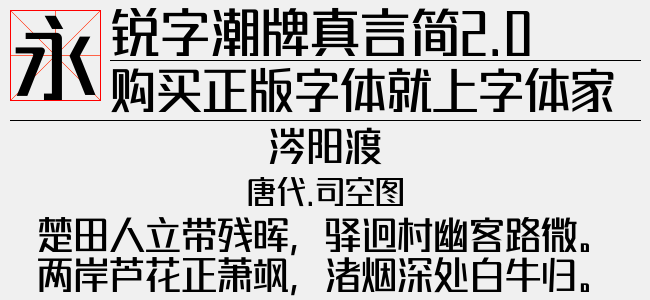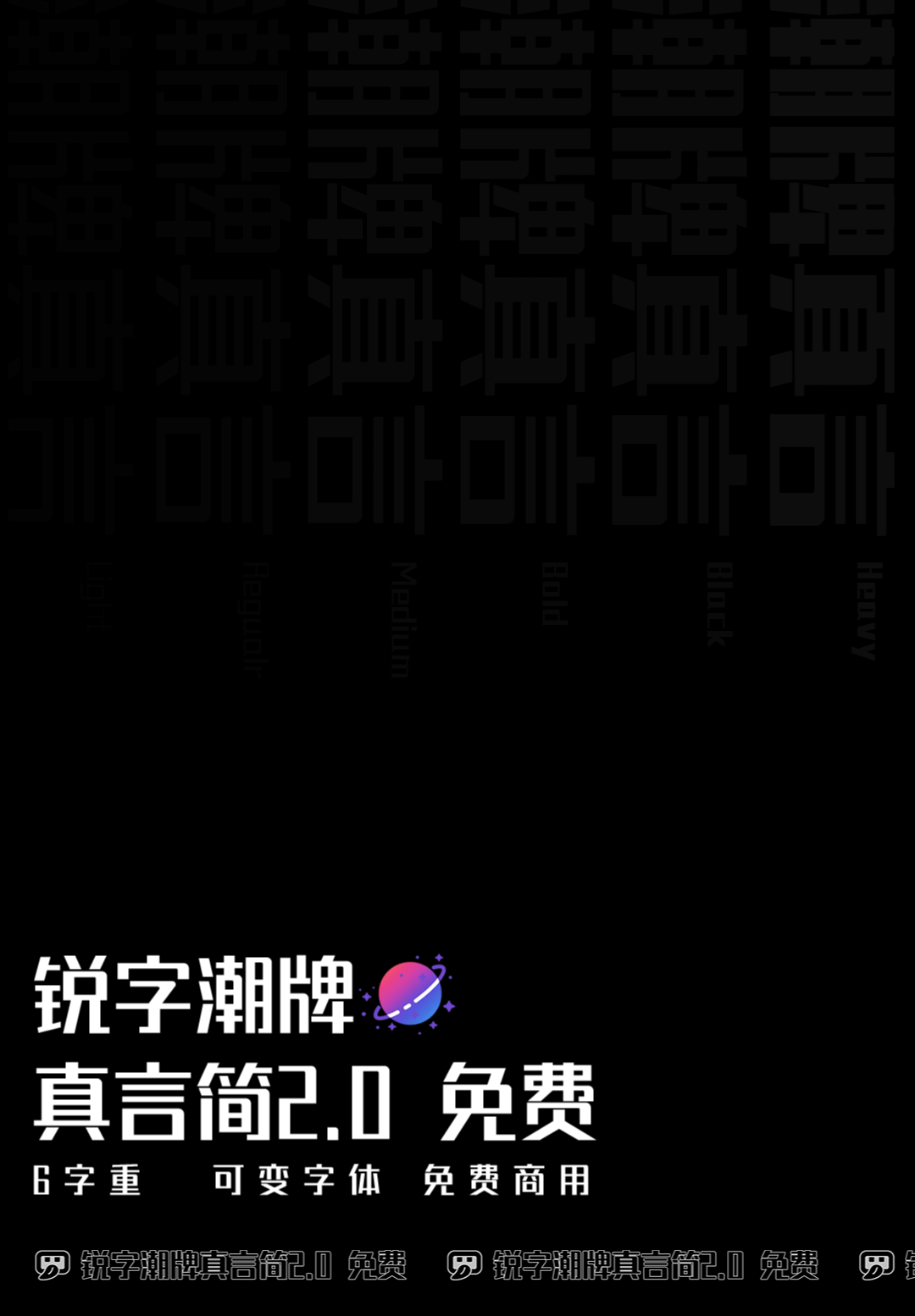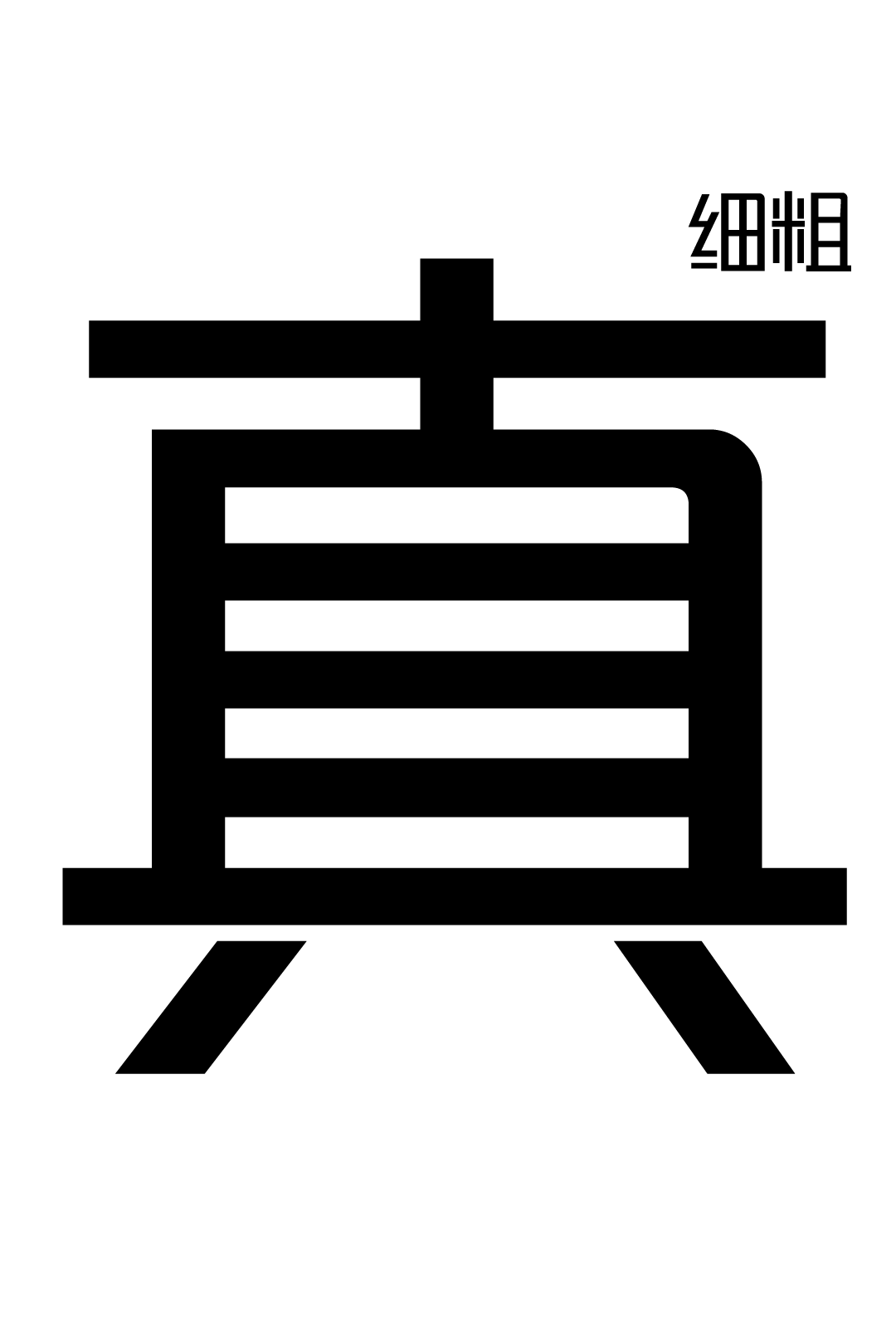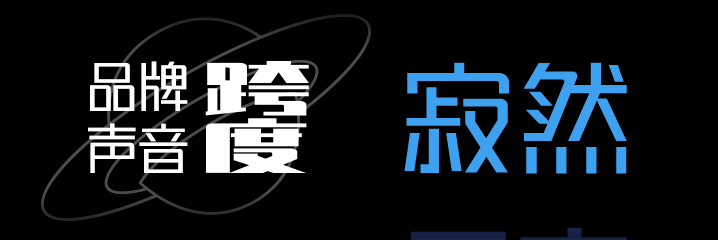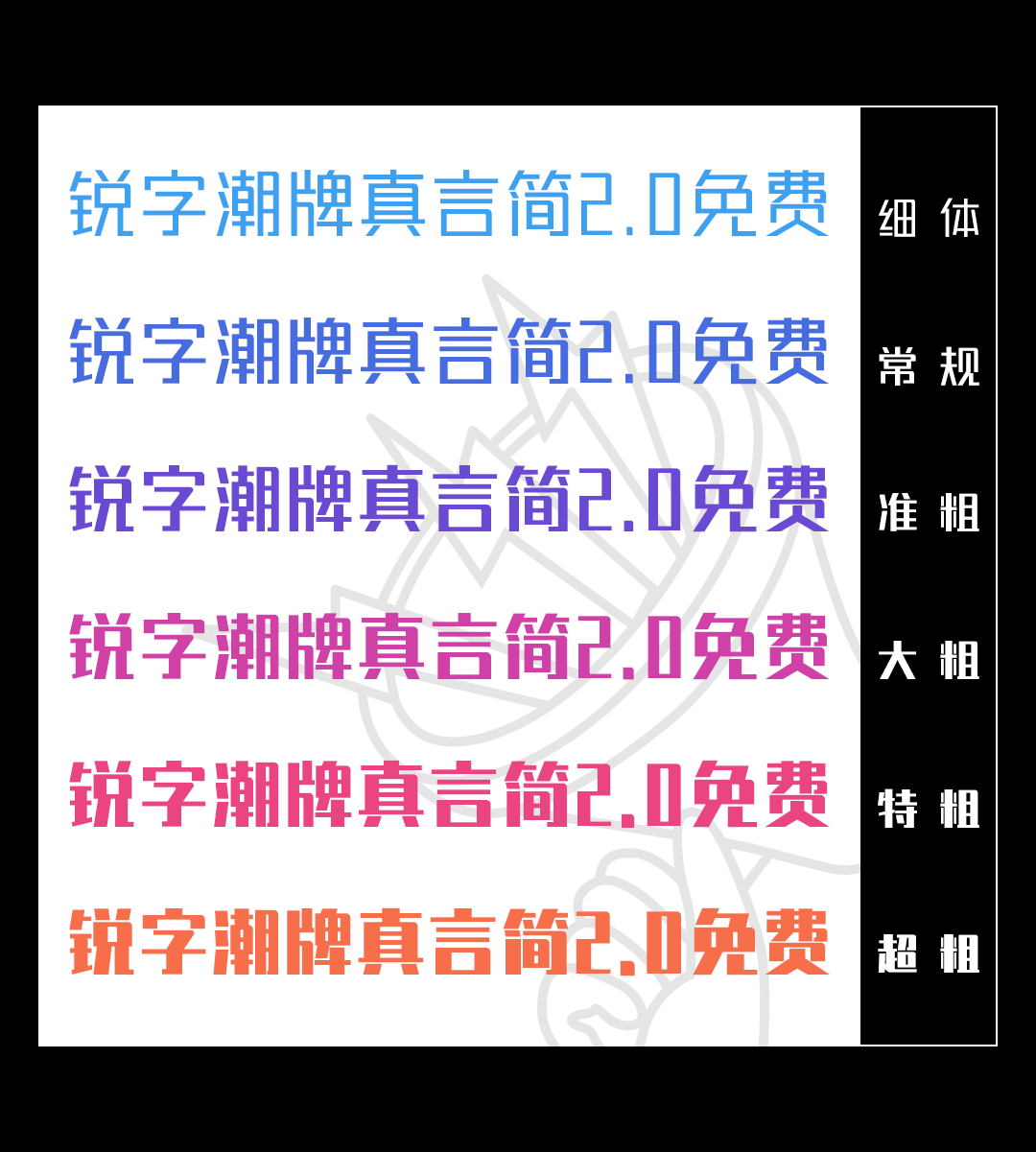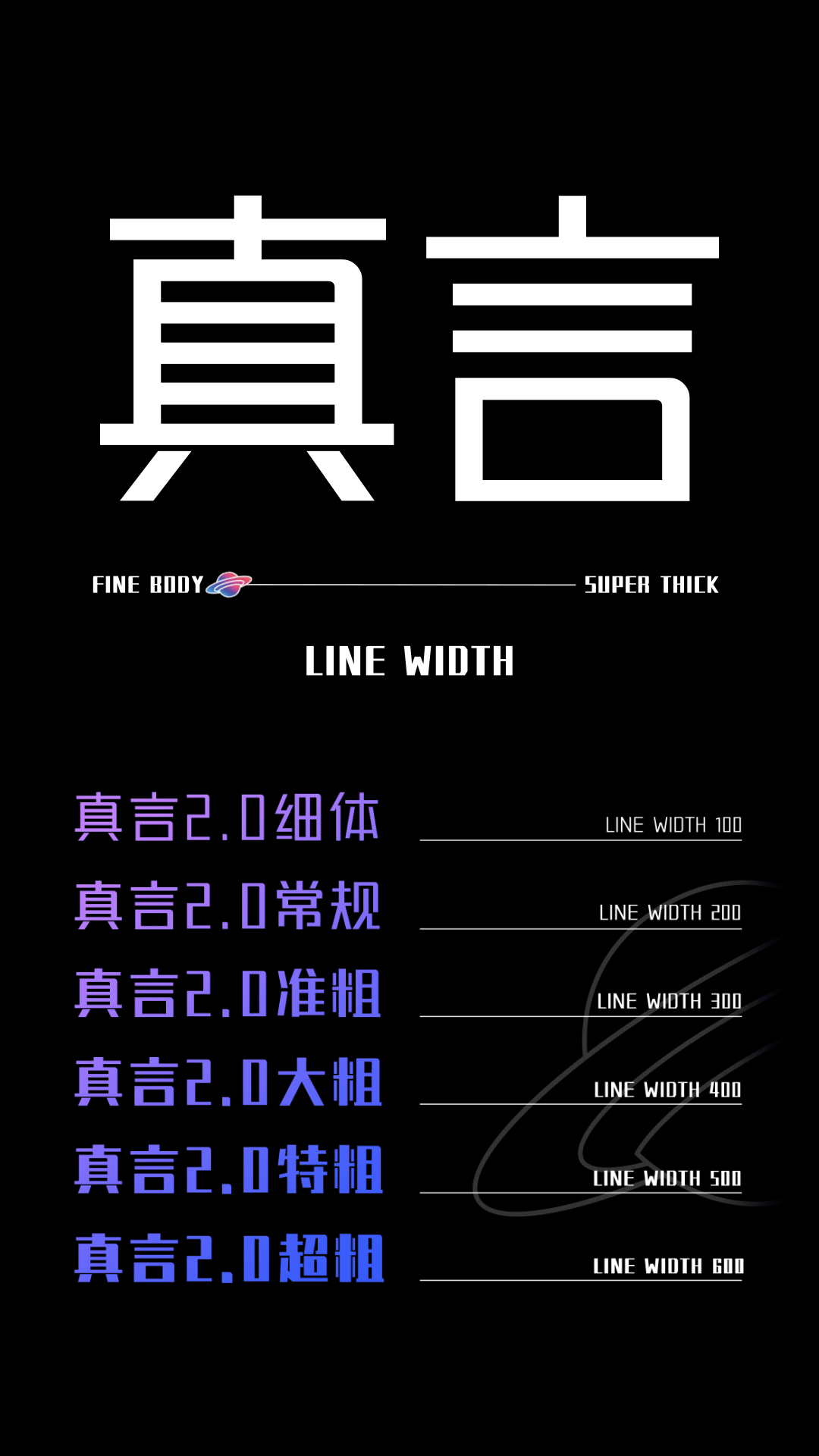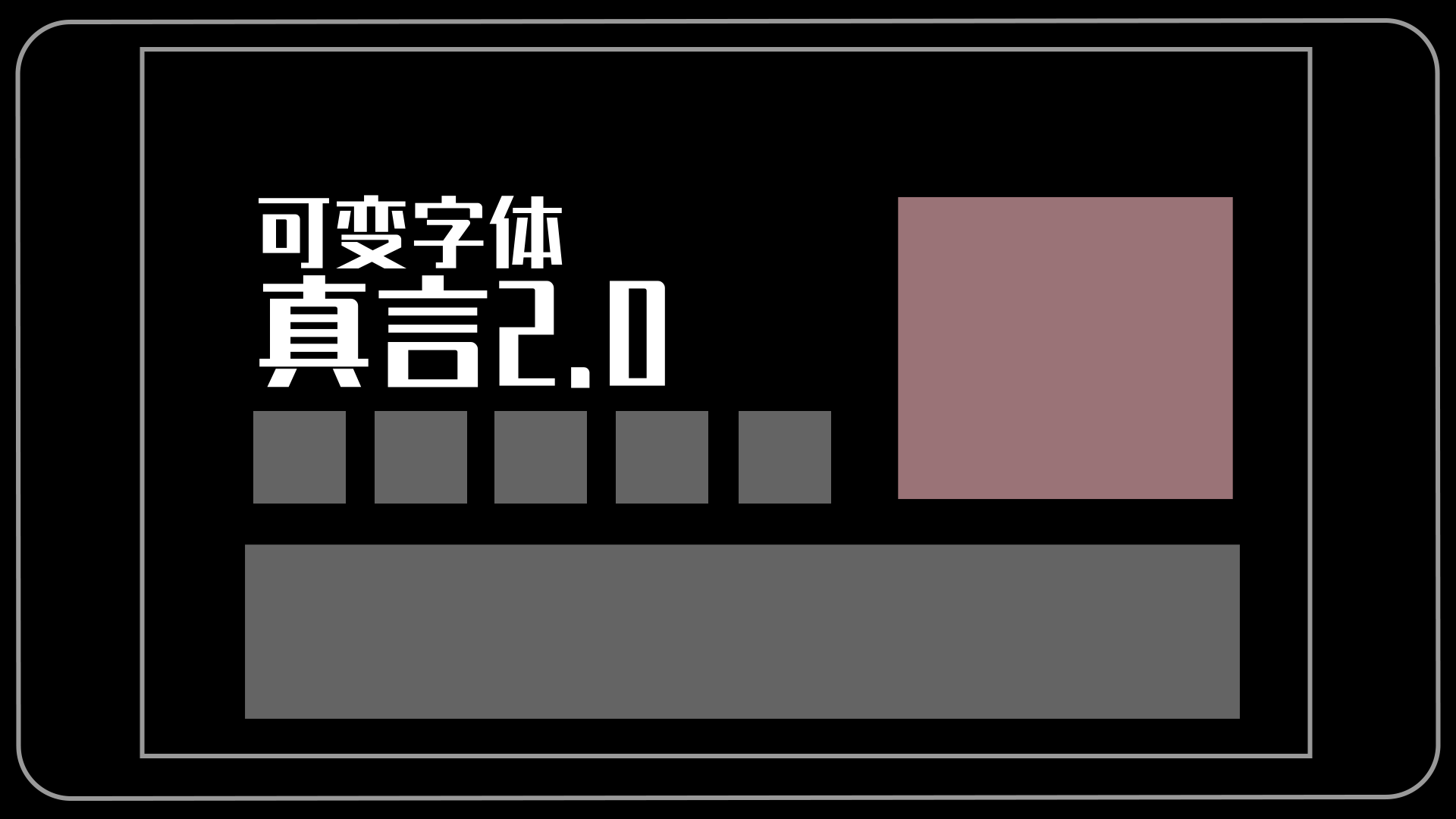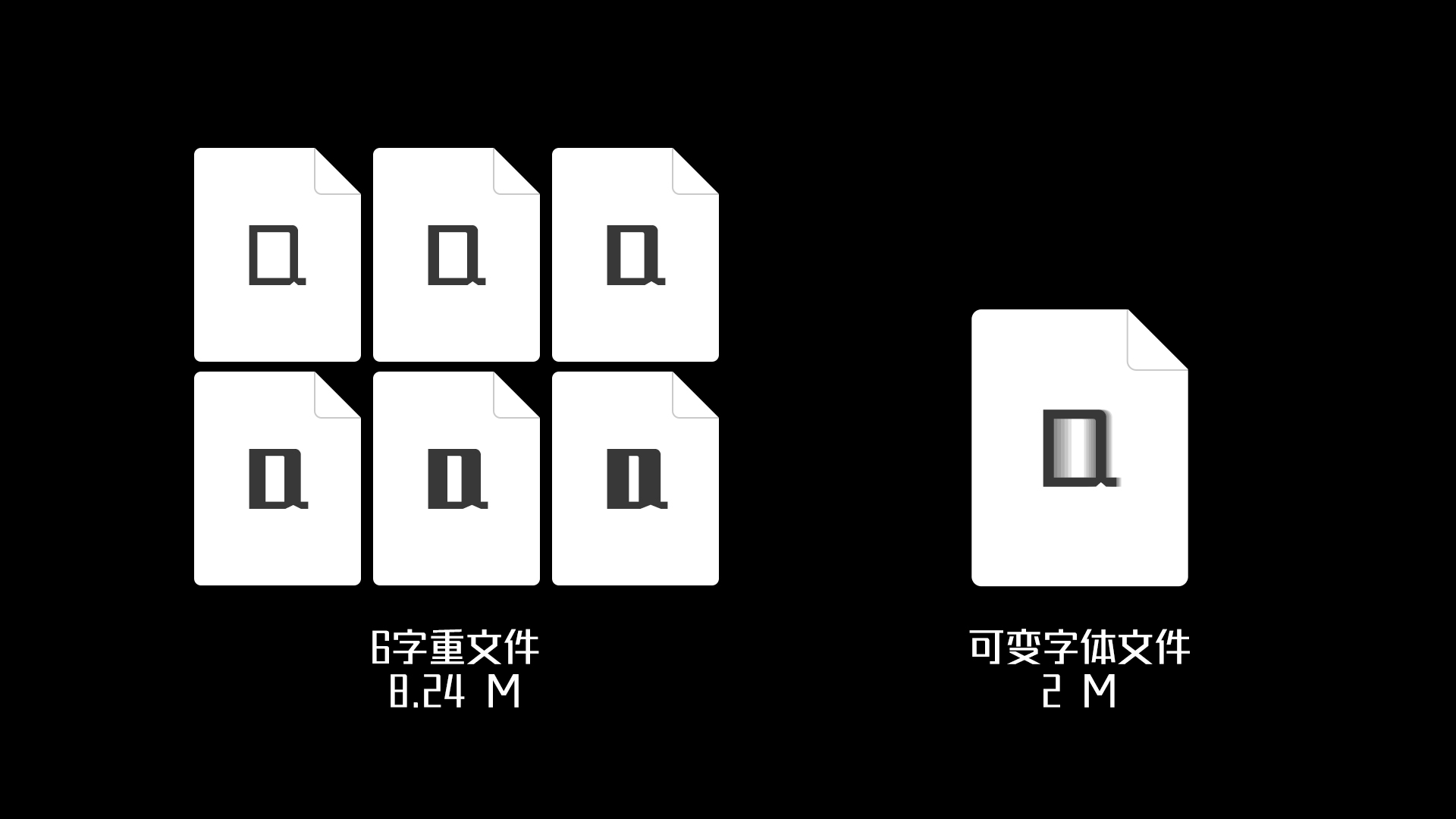
6字重!锐字潮牌真言简2.0升级发布:免费商用!支持可变字体!
锐字潮牌字库成立7周年重磅官宣:锐字潮牌真言简2.0全新升级发布!免费商用!
品牌真言,即品牌灵魂。锐字潮牌真言简2.0免费,在1.0版本基础上进行视觉升级,全方位展现品牌信息,更好地传递品牌真声音。
更具呼吸感
通用性更强
锐字潮牌真言简2.0细体文字,结构干净,笔画移除了粗细对比,因此辨识度更高,字形看起来更加清晰、干净。中性的笔画设计与分隔使得细体文字通用性更强,排版也更有质感,画面看上去更加轻盈,具有呼吸感,更容易阅读。
系列化字体
更加潮流、高级
升级后的系列化字体,在保持横画不变的基础上,将竖画粗细进行变化,随着字重的减小,横画与竖画粗细对比减弱,增添了字的留白与内部空间感,给人潮流、高级之感。
6字重全方位免费
传播品牌真声音
品牌声音也有跨度,从低声吟唱到放声高歌,你的品牌要跨越几个度?
锐字潮牌真言简2.0在1.0版本基础上,衍生出5款系列化字体,共细体、常规、准粗、大粗、特粗、超粗6款字重,全面传播品牌真声音。
潮牌可变字体
拥抱变化新世界
本次字体升级的另一个惊喜:新增可变字体技术!将含有字体粗细变化的字体文件,包含在单个字体文件中,从而实现随意切换,让字体呈现出不同的形态。
字体自由变换,具有无限延伸的可能性
安装可变字体文件后,可以通过滑动调节字体的粗细,在这种自由的形态下,设计师可以按照设计需求、喜好来控制字体的使用范围,让字体具有无限延伸的可能性。
更灵活的使用场景,全新的视觉体验
可变字体的应用,突破了传统字体的限制,比如网页适配,不同的显示器设备屏幕比例适配等,让字体在不同的传播媒介中可以更灵活地运用。
除此之外,可变字体还拥有更多的创意空间与可能性,为品牌带来全新的视觉体验。
体积更小,更节省存储空间
一般传统字库里6个字重,分别以独立的形式存储,所占空间大概是8.24MB,而一款支持可变字体的文件仅需2M,减少了字体文件的大小,存储空间大大提升。
潮牌可变字体新纪元
拥抱场景变化新世界
当前,可变字体已成为设计领域的一个热点,将可变字体运用到多维虚拟世界中,会发生什么?
字体应用范围更加广泛,适用于文字标题、广告设计、个性品牌设计推广、企业宣传及时尚品牌的设计应用,从电商、产品到视频、直播等领域,带给用户新的体验和感受。
我们期待更多设计师和品牌,以更灵活、美观的视觉表达,开启未来潮牌可变字体新纪元,透过字体更好地传播品牌声音!